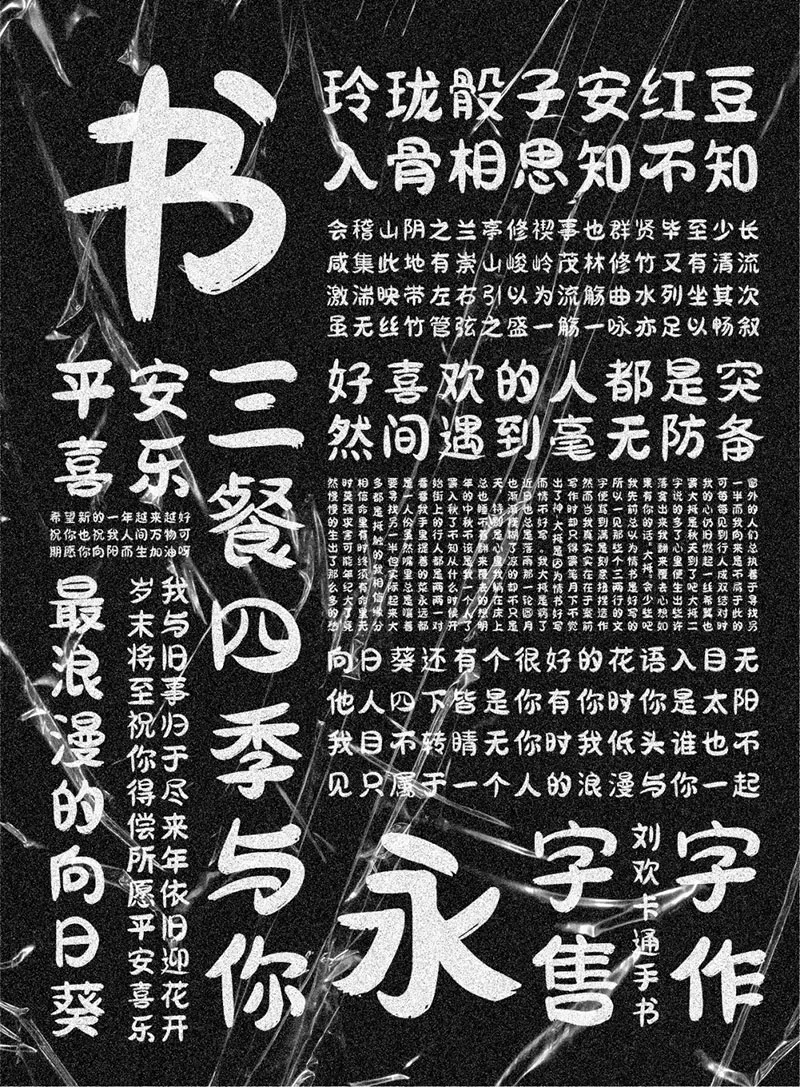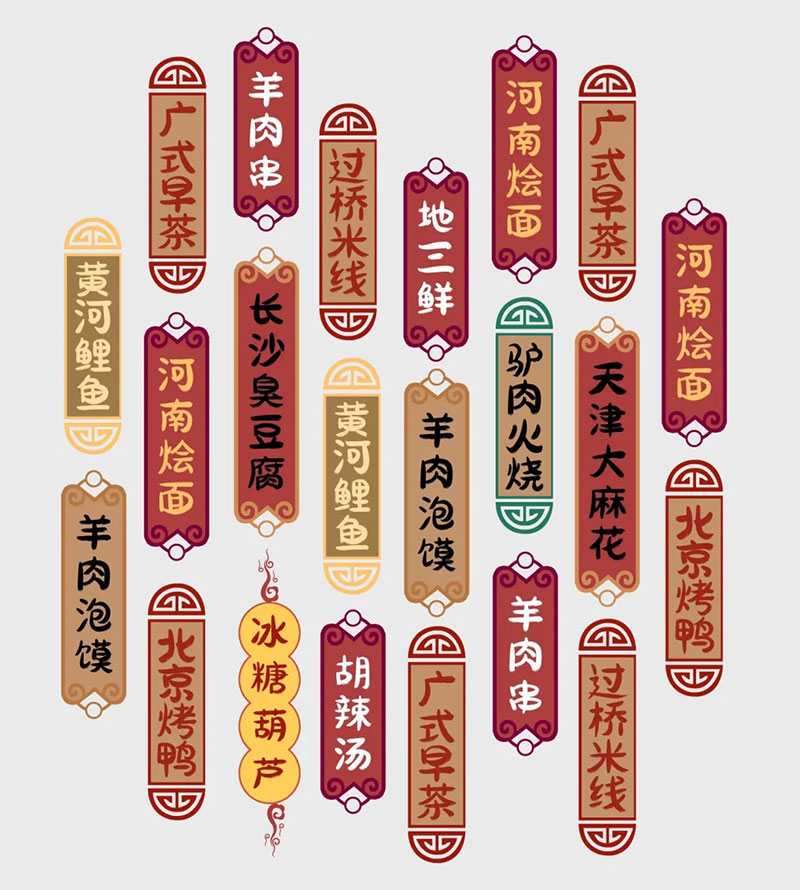
劉歡卡通手書預覽
劉歡卡通手書介紹
2018年初,接觸到字體設計,就被漢字的演變深深吸引,一向不愛寫字的我才發現:原來漢字還可以這麼美!
其實說起這套字庫的創作初衷,是因為當時找的工作不合適然後回家了…
當時實習選擇去了離家還算近的上海。全球最現代化的大城市之一,紙醉金迷的大上海,繁華程度已經超過東京和紐約。土狗進城,見到了很多新奇的事物,不愧是很多年輕人嚮往的魔都!
一個沒見過世面的農村小夥子,見到了繁華的夜都市和車水馬龍,以及熙熙攘攘的業界精英。我也想過在上海拼搏闖出一片屬於自己的小天地,奈何實力不濟,上漂了不到兩個月,找不到自己適合的工作,最終還是回家了。
與其說,不合適,其實還是自己沒有足夠的實力,哈哈。也許,每個有血性的年輕人都是這樣吧,見到了大城市的繁華又怎麼甘心回到小縣城呢。
到家以後,父母和親戚都為我的工作而著急,都21歲了天天待在家裡,鄰居會怎麼看?我想要提升自己的水平方便以後找工作,就以考完駕照再出去的理由在家順利待了一段時間。
就是那段時間,在家瘋狂惡補版式、插畫、剩下時間就是練字了。
事實證明,在家待久了,確實被鄰居嘲笑了……然後父母也不能理解自己。不出去找工作,每天在家亂寫亂畫的有甚麼用,為此也爭吵了很多次……
溝通不了,還是想著能提升自己最好。繼續待在家裡!也可以說是寫字讓我有了對未來憧憬的動力。
說起字庫,對於知識產權,版權問題是不可避免的,剛入門的設計師,難免會因為不懂版權,對自己或對公司而言,這幾年的版權新聞鉅額罰款也是不斷出現,造成不可挽回的損失。想著寫了就寫一套字庫出來,也算為社會盡自己的綿薄之力。
既然決定了就開始,每天除了吃飯就待在屋裡寫字,頂著壓力,寫了又寫,改了又改,寫了幾種字樣,最後定了這一款卡通字體。到2020年12月初全部寫完。
到月底拿著自己的這套字庫在測試的時候,開心的一整晚沒睡著!
現在只想對當時的自己說:孤獨是常有的,興趣和理想卻不是,小時候的夢想好多好多,現在你還記得嗎?一個人前行時,甚麼都可以丟棄。目標不能丟,耐受不了寂寞,鹹魚翻身的機會都少有。
下面來看字體展示,起名“卡通”字體,其實用作“標題字”也是OK的。
所有筆畫以“圓潤”為主,保留少量飛白,在屏幕上顯示更佳。同時在線下使用也不缺失手寫韻味。該字庫不限制使用場景,印刷書籍除外,不適合太小的字體展示。